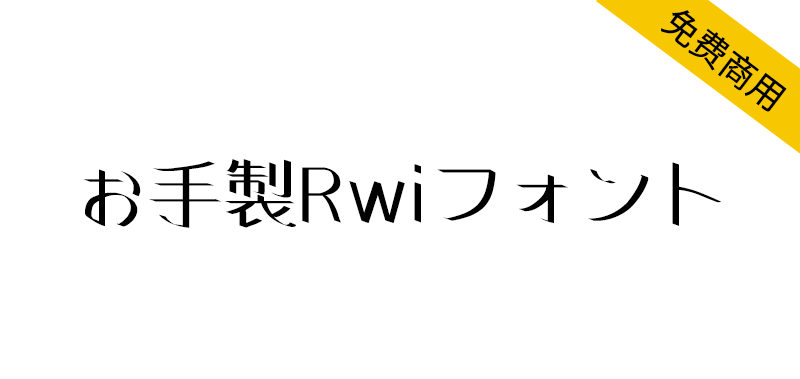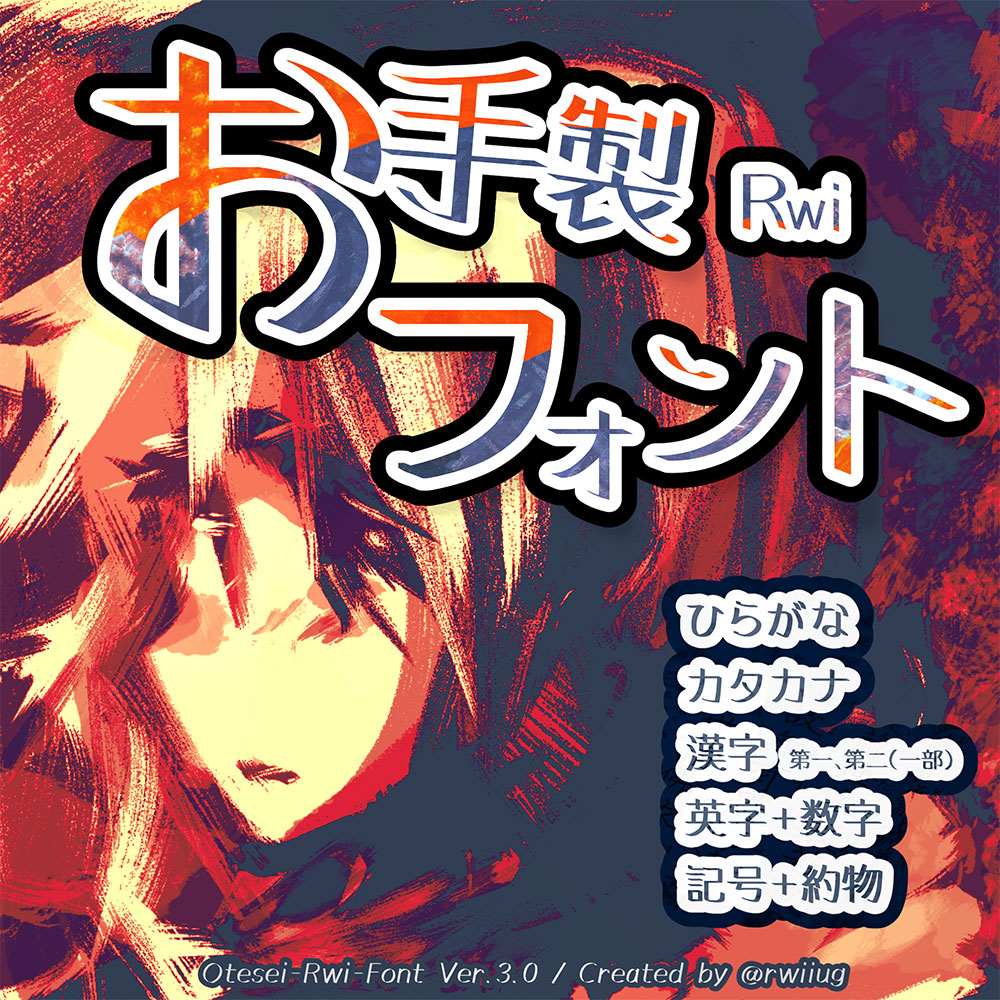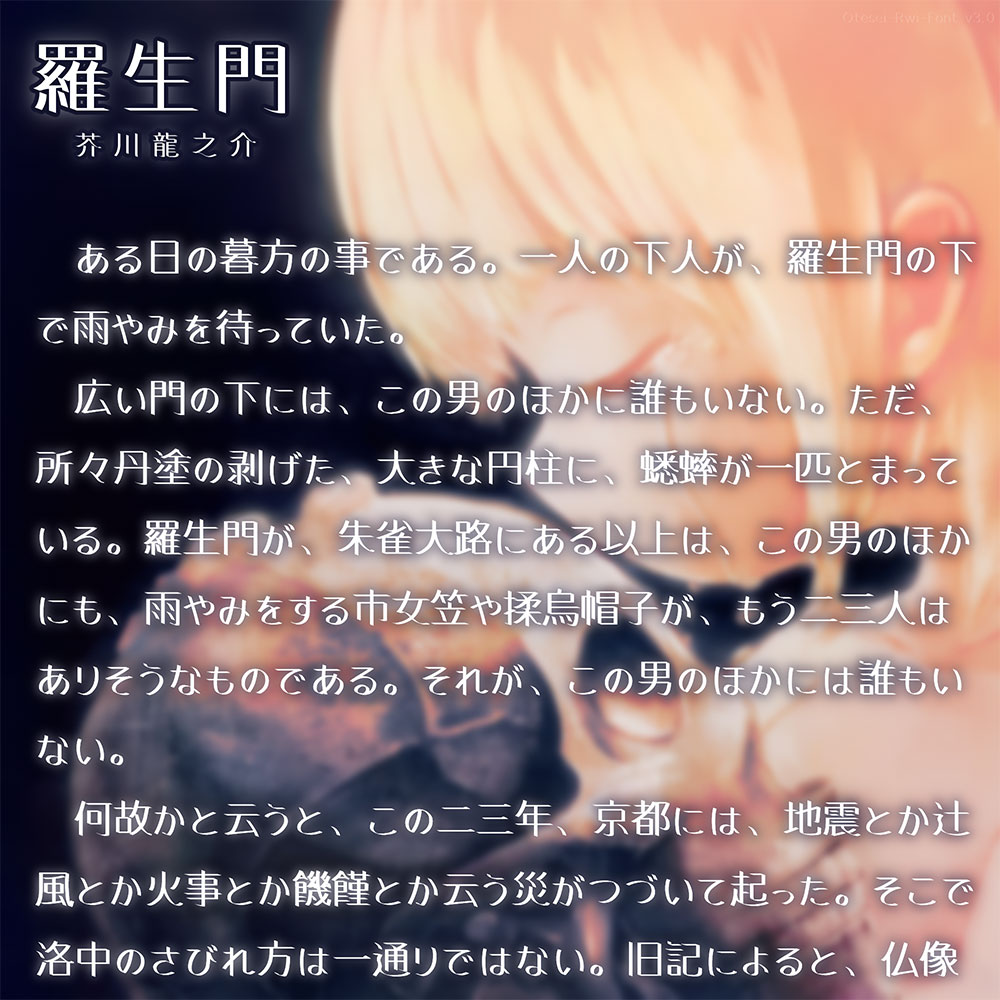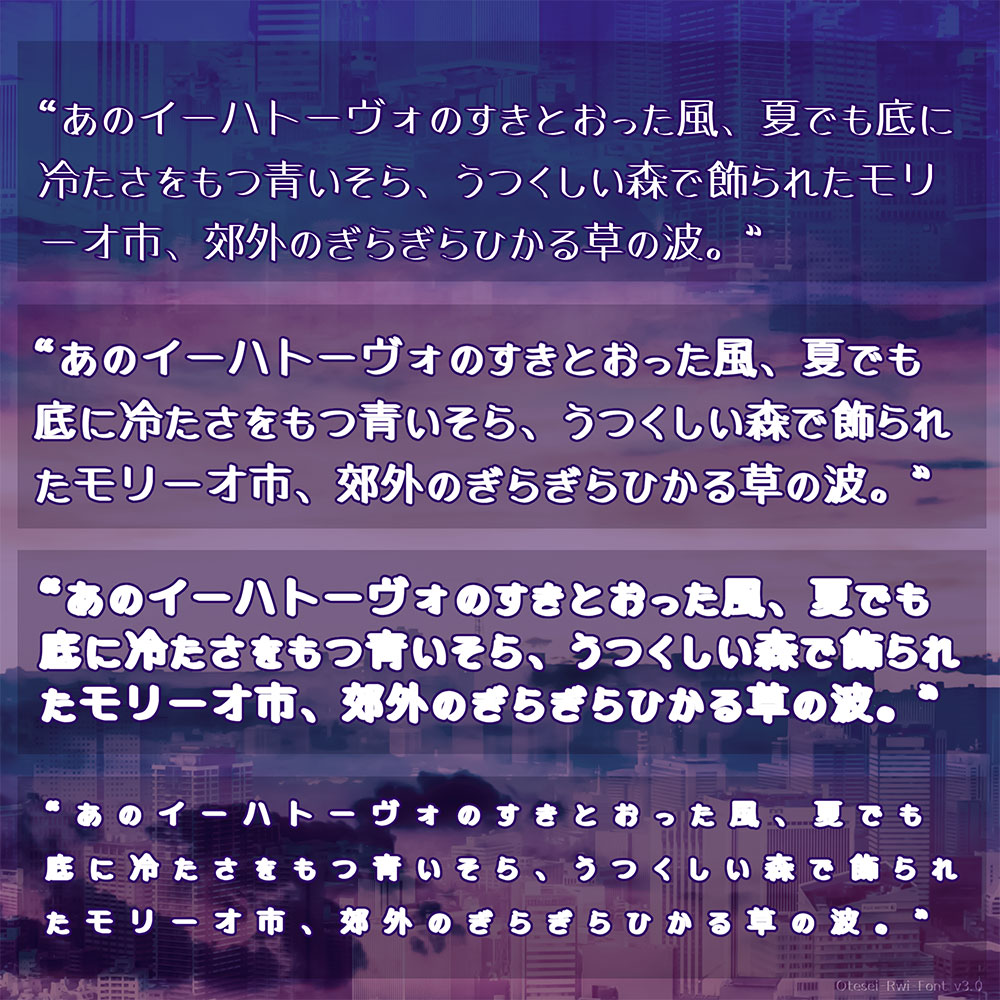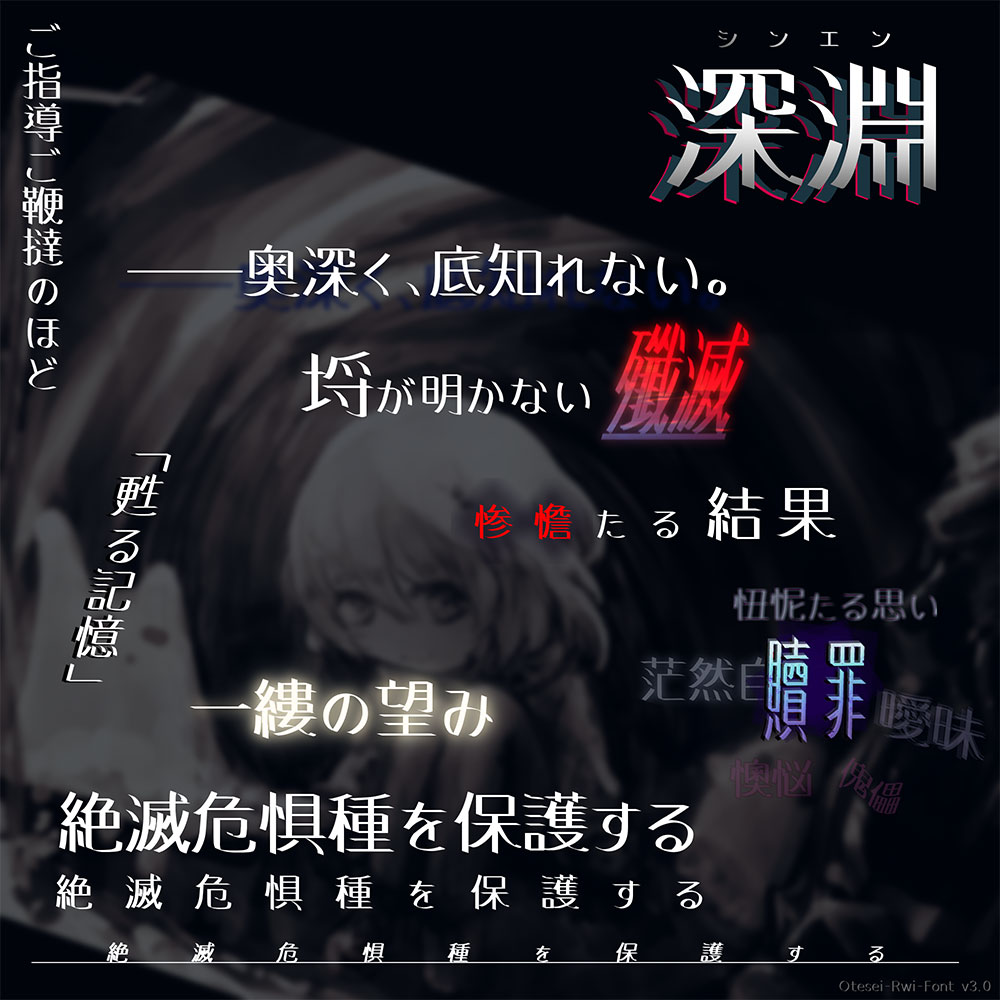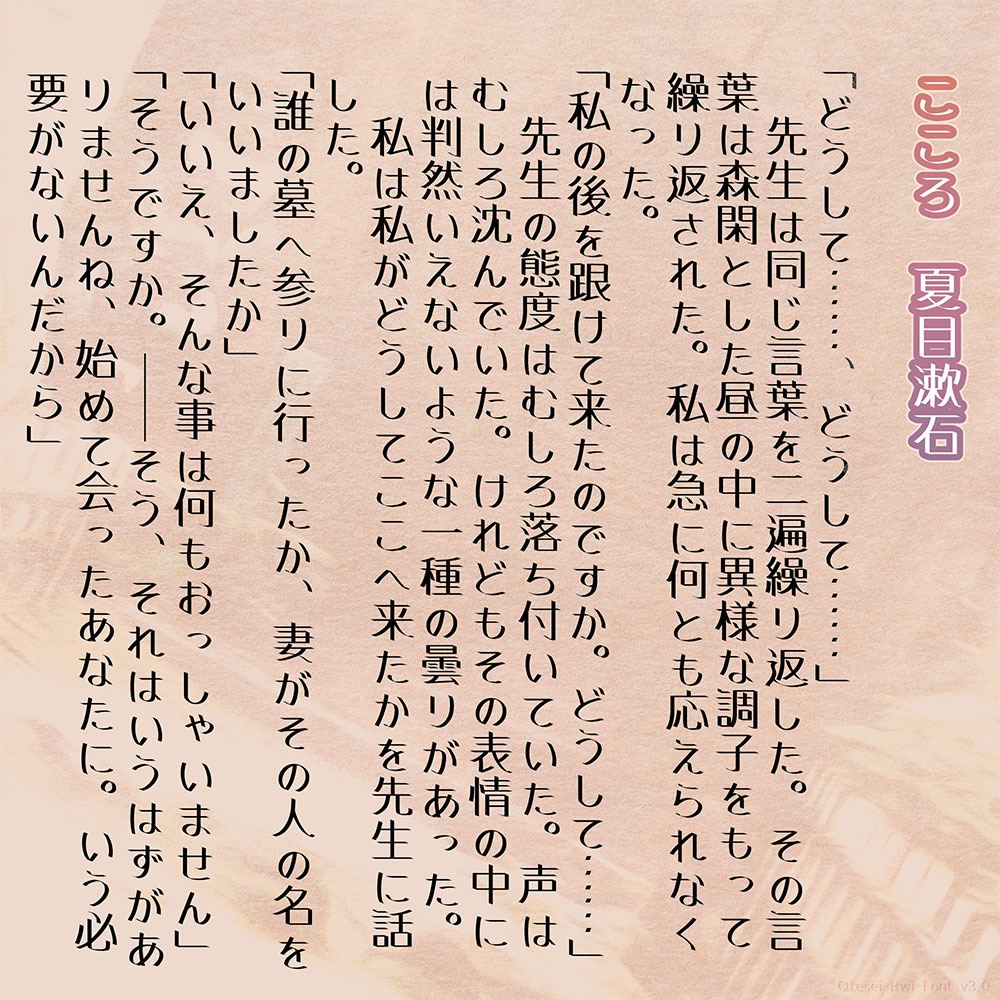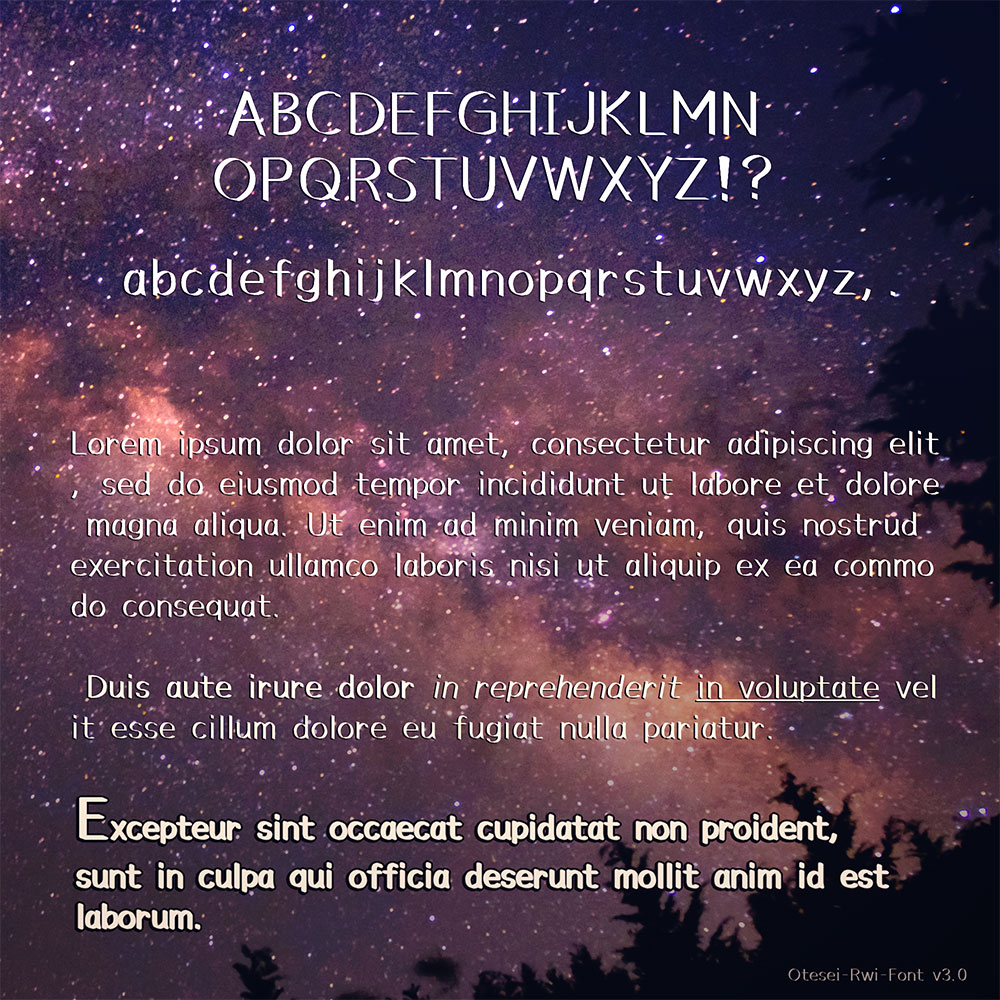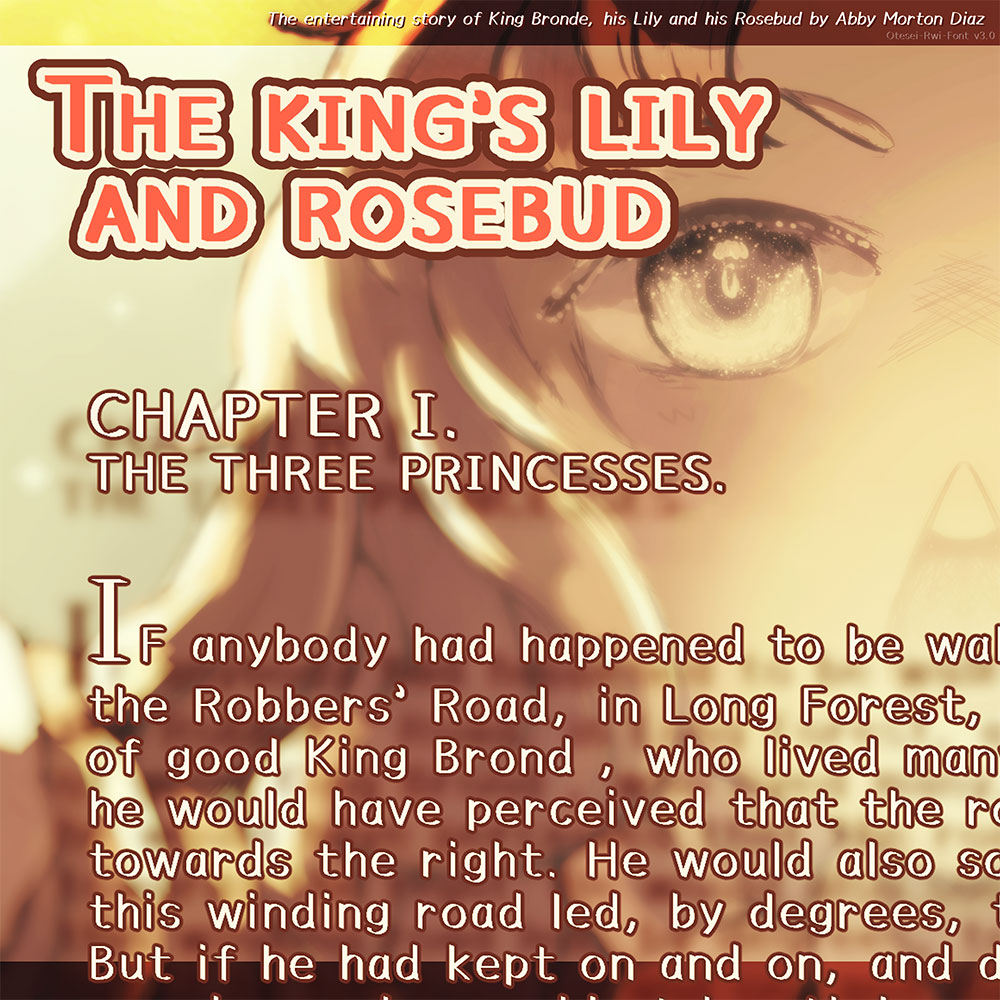
【お手製Rwiフォント】具有强劲的笔触和独特的柔和味道
你见过既刚劲有力又带着独特柔和韵味的手写字体吗?这款基于M+ FONTS逐笔重绘的【お手製Rwiフォント】,由创作者亲手刷写每个字形并精细调整,风格极具辨识度。更棒的是——它免费商用!遵循SIL OFL 1.1协议,可自由使用、分享甚至修改,只需不单独售卖字体文件。设计师、开发者、内容创作者都在找的高性价比字体解决方案,就在这里。
【お手製Rwiフォント】具有强劲的笔触和独特的柔和味道
お手製Rwiフォント是一款以M+ FONTS字体为基础,用自己的笔划刷一个字一个字地手写并在软件上进行了调整制作,具有强劲的笔触和独特的柔和味道。